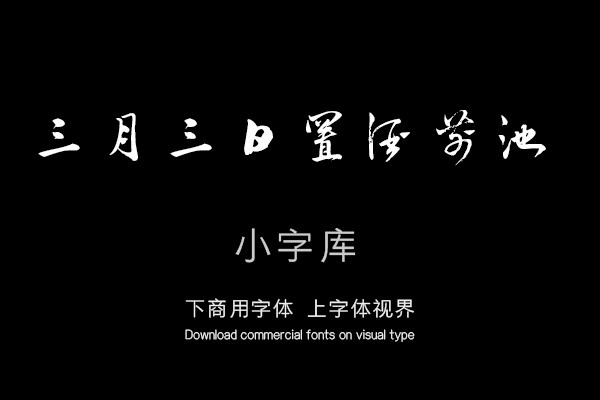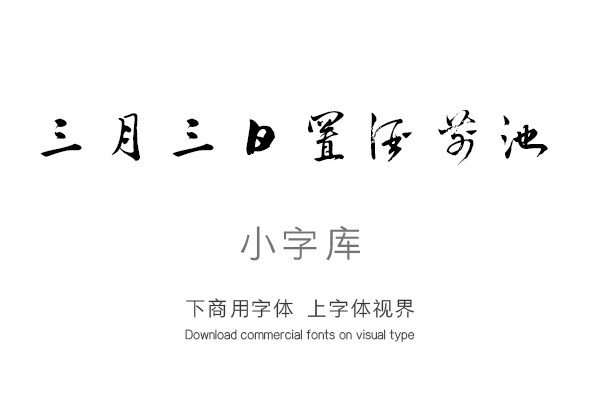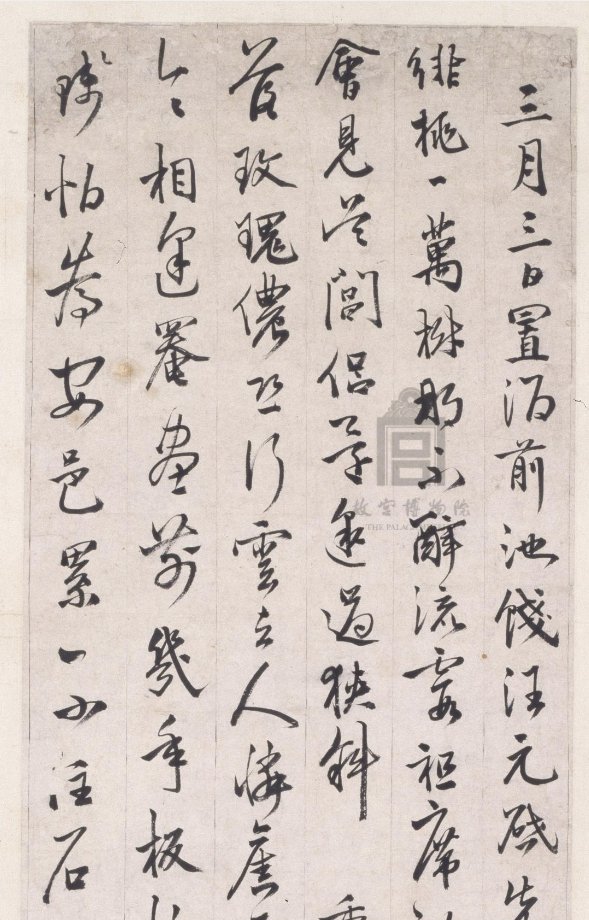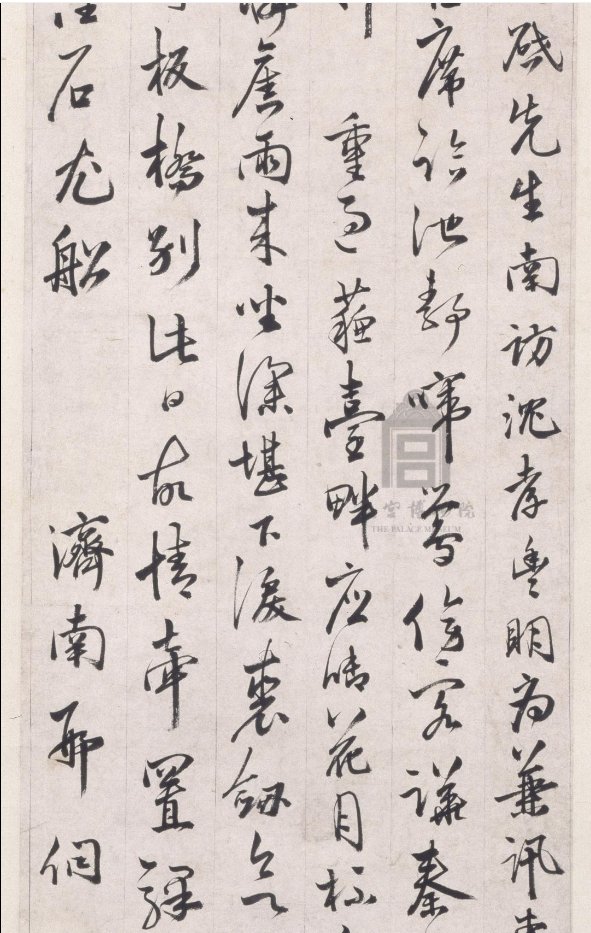
汉标邢侗饯汪元启诗
《汉标邢侗饯汪元启诗》是一款根据明代邢侗经典书法作品《饯汪元启诗》,经过再次调整制作的小字库,该小字库共收录了该真迹作品中约181个字体。
三月三日置酒前池,饯汪元启先生南访沈孝丰明府,兼讯东吴王百糓诸公。徘桃一万树,那不醉流霞。袒席临池静,啼莺傍客譁。秦邮家亦寄,越耶路非赊。会见吴阊侣,还邀过狭斜。重过苏台畔,应啣花月杯。舞鸾惊飒沓,弹鹰落玫瑰。侬恐行云去,人怜旧雨来。坐深堪下泪,裘剑欲藏摧。泽国栽花令,相逢罨画前。几年板桥别,此日故情牵。置驿分官酒,倾囊损俸钱。怕荐安邑累,不注石尤船。济南邢侗